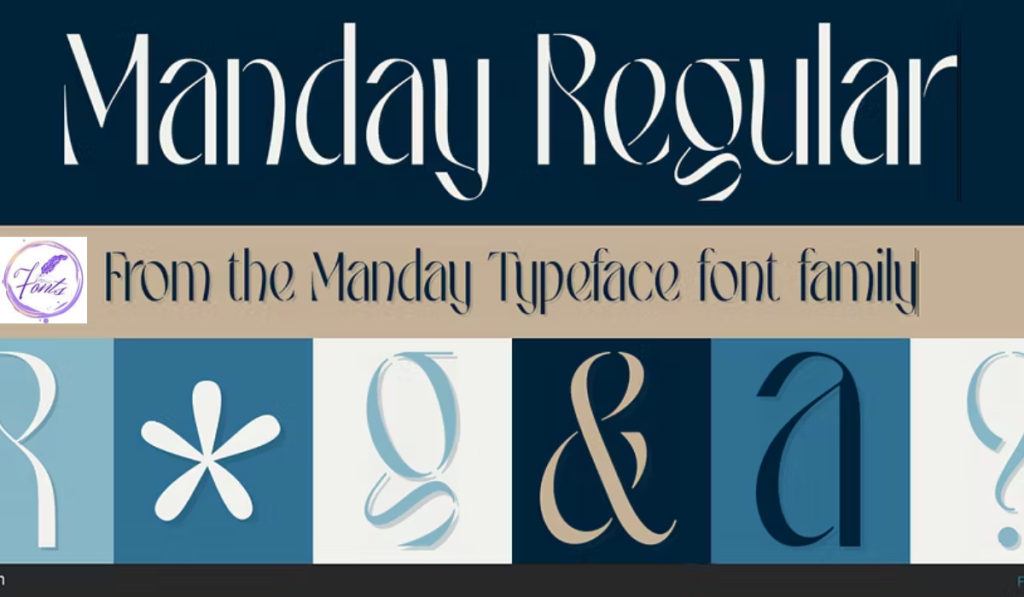
Font Manday Typeface Việt hóa
Tác giả: Alit Design
Ngày phát hành: 2022
Ngôn ngữ: Tiếng Việt và một số ngôn ngữ khác
Bộ Font: Manday Typeface
Phân loại: Hiện đại, Độc đáo
Kiểu chữ: Không chân
Font Manday Typeface là một trong những kiểu font độc đáo được thiết kế để mang lại sự mới lạ cho các dự án sáng tạo. Với thiết kế hiện đại và nét chữ thanh lịch, Manday được việt hóa để phù hợp hơn với người dùng Việt Nam, làm cho nó trở thành lựa chọn hoàn hảo cho cả thiết kế in ấn và thiết kế web. Font này đặc biệt thích hợp cho các dự án branding, thiệp mời và quảng cáo nơi cần một phông chữ nổi bật và thu hút.
Đánh giá Font Manday Typeface
Font Manday được đánh giá cao bởi cộng đồng thiết kế không chỉ vì vẻ ngoài đẹp mắt mà còn vì tính linh hoạt của nó trong việc sử dụng. Các nhà thiết kế thường sử dụng Manday trong các công trình từ trang trí nội thất đến sách bìa và poster nghệ thuật. Khả năng tùy chỉnh cao và sự dễ đọc giúp font này trở thành sự lựa chọn hàng đầu cho các dự án yêu cầu sự thanh lịch và tinh tế.